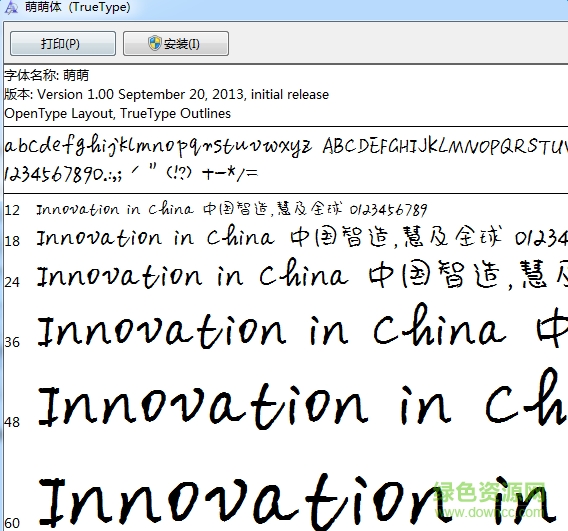
伯樂(lè)自然萌體
伯樂(lè)自然萌體字體是一款超好用的中文個(gè)性字體,該字體非常萌,給用戶(hù)的平面設(shè)計(jì)帶來(lái)了一絲活力,讓廣告宣傳更有效,歡迎來(lái)綠色資源網(wǎng)下載。
伯樂(lè)自然萌體字體
伯樂(lè)自然萌體字體是一款極具個(gè)性的字體,該字體十分飄逸,彰顯了自己的個(gè)性,有喜歡的朋友可以來(lái)綠色資源網(wǎng)下載使用!